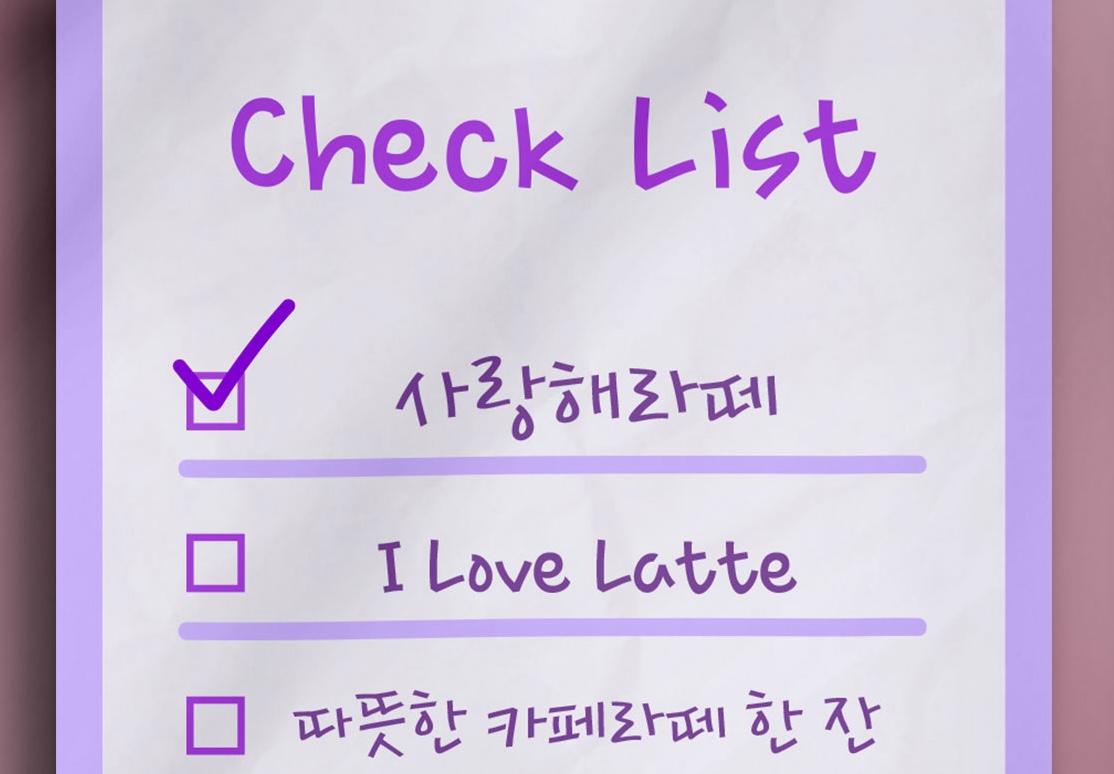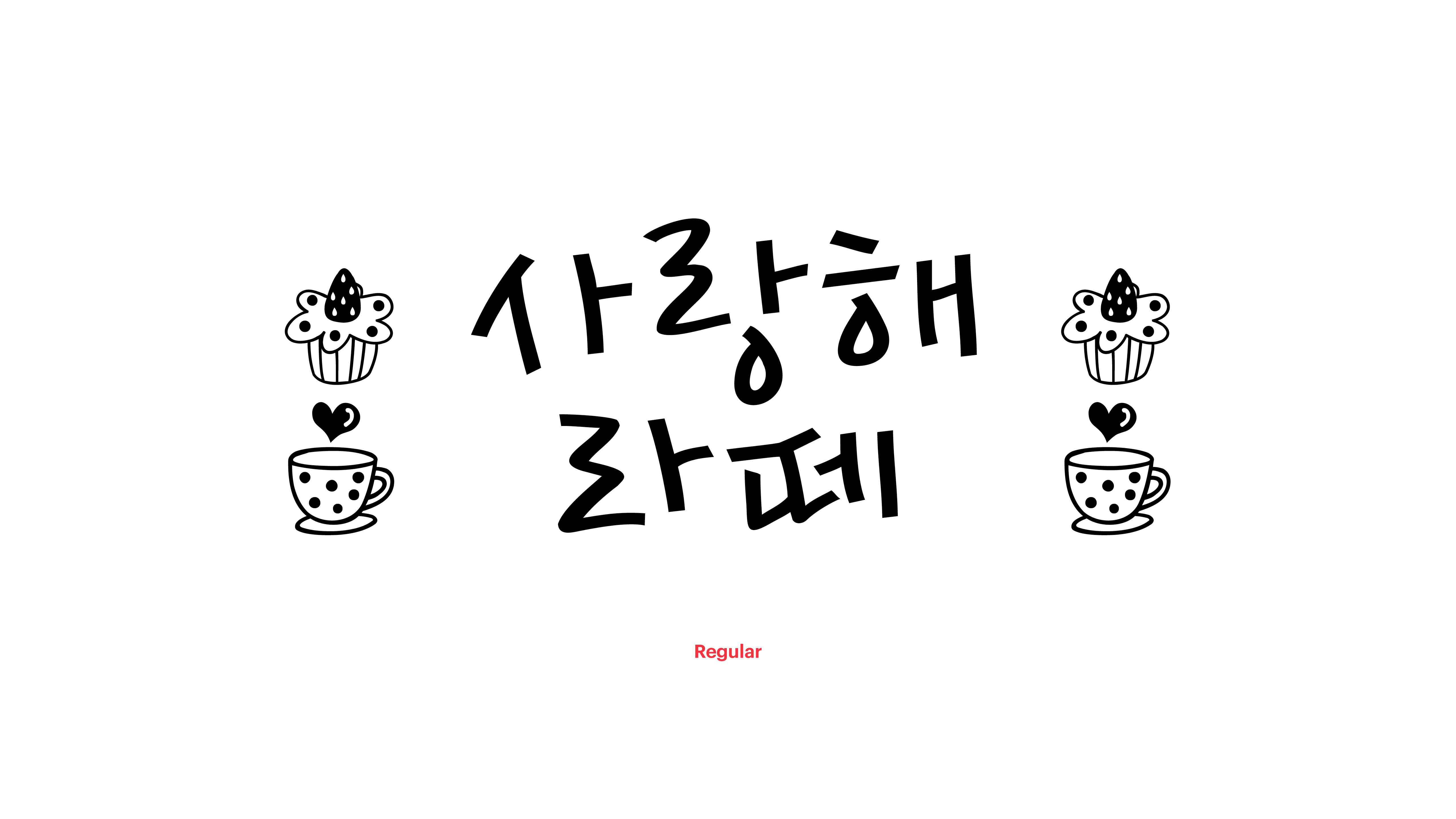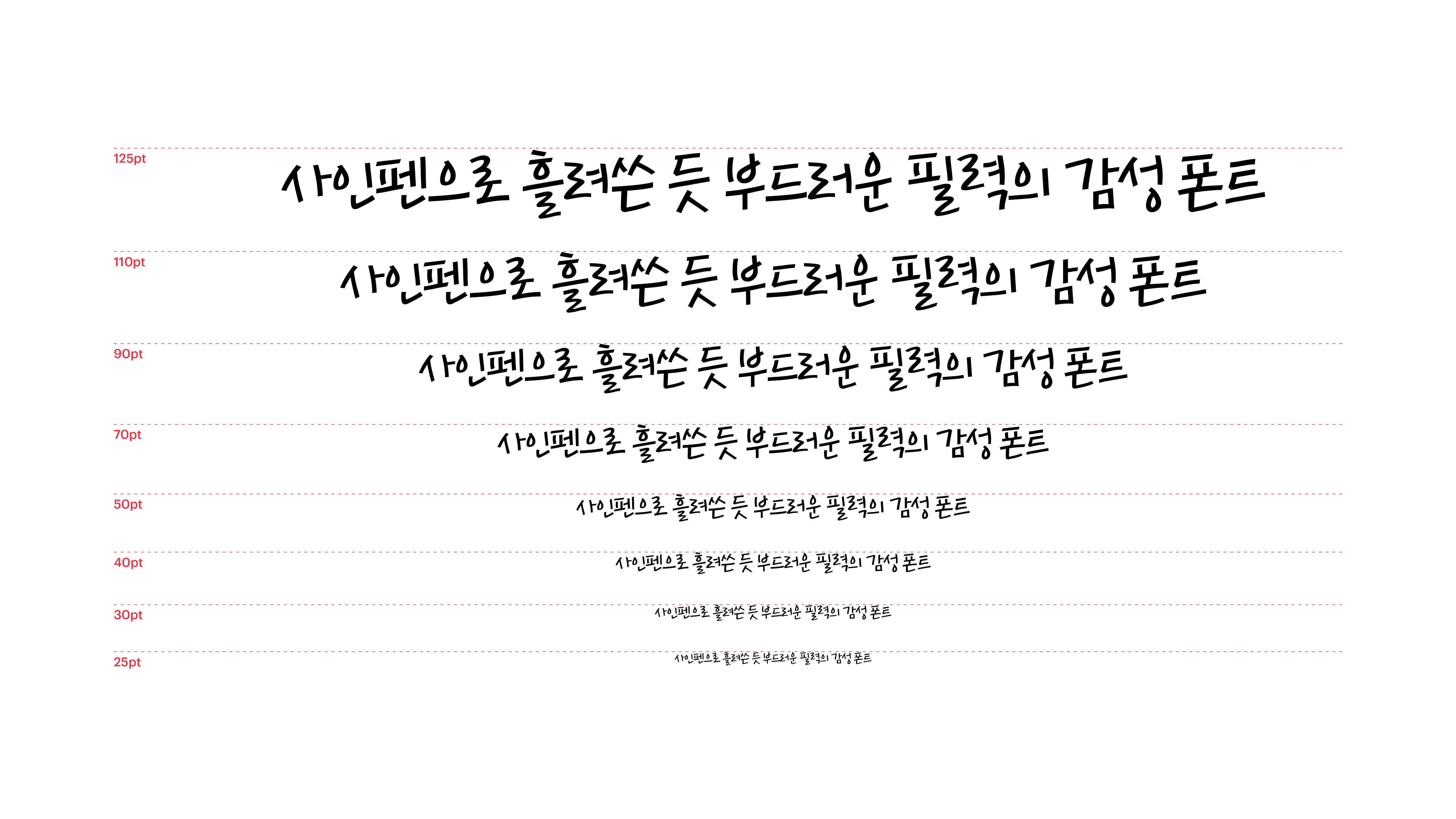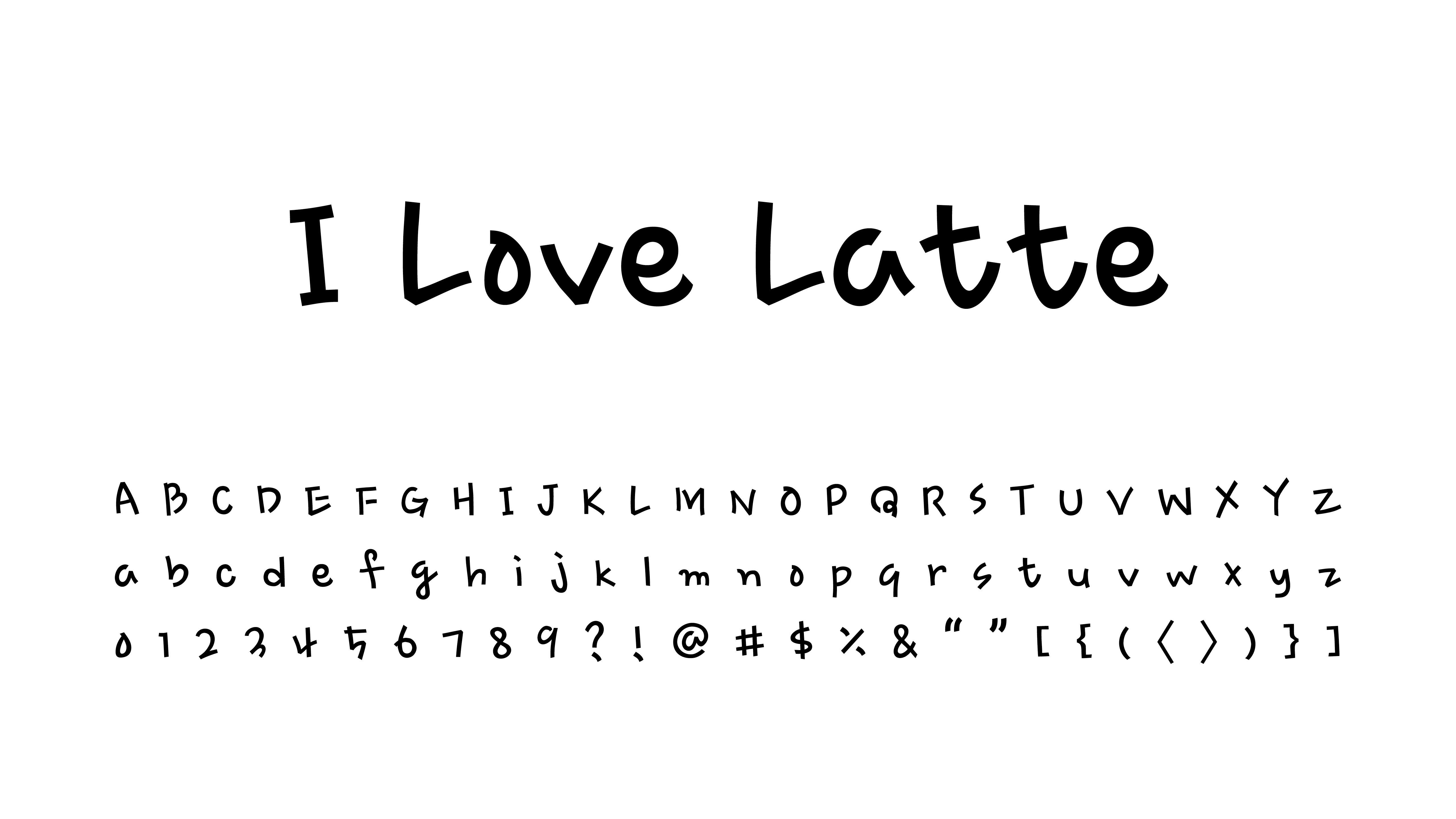
“따뜻한 카페라떼 한 잔, 우유 거품 많이요.” 비 오는 날 카페에 앉아 있으면, 들어오는 사람마다 비슷한 주문을 합니다. 촉촉한 비의 감성에 폭신하고 고소한 커피 한 잔을 더하고 싶은 날이니까요. 따뜻한 커피로 몸과 마음을 녹이며 머리 위로 안 보이는 창을 하나씩 띄우는 사람들. 사인펜으로 써내려간 듯 부드러운 이 폰트로 그리운 사람의 이름을 적어보고 있는지도 모르겠어요.
Yoon 사랑해라떼